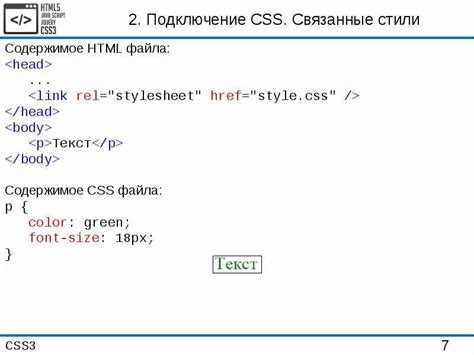
Выбор шрифта напрямую влияет на читаемость и визуальное восприятие веб-страницы. В HTML шрифты можно подключать через встроенные, системные или веб-шрифты, при этом каждый способ имеет свои особенности совместимости и производительности. Использование системных шрифтов гарантирует мгновенную загрузку, но ограничивает дизайнерские возможности.
Веб-шрифты подключаются через сервисы вроде Google Fonts или через локальные файлы формата .woff и .woff2. Для подключения через Google Fonts достаточно вставить тег <link href=»URL_шрифта» rel=»stylesheet»> в head документа и использовать имя шрифта в CSS с помощью свойства font-family. Локальные шрифты подключаются через @font-face с указанием пути к файлу, формата и веса.
При выборе метода подключения важно учитывать скорость загрузки и поддержку браузеров. Формат .woff2 обеспечивает лучшую компрессию и поддерживается современными браузерами, в то время как .ttf и .otf совместимы с более старыми версиями. Рекомендуется всегда указывать запасной шрифт через font-family, чтобы избежать некорректного отображения текста при проблемах с загрузкой основного шрифта.
Правильная организация шрифтового кода повышает стабильность отображения и уменьшает нагрузку на сервер. Использование локальных и веб-шрифтов одновременно позволяет обеспечить баланс между дизайном и производительностью, особенно на мобильных устройствах с ограниченной скоростью интернета.
Выбор шрифта для веб-проекта
При выборе шрифта важно учитывать читаемость, совместимость и контекст использования. Для текста основного контента оптимальны гарнитуры с засечками (serif) для длинных абзацев или без засечек (sans-serif) для краткой информации и интерфейсов. Например, для статей подходят шрифты Georgia и Times New Roman, а для кнопок и меню – Roboto, Open Sans, Lato.
Необходимо учитывать поддержку браузеров и операционных систем. Google Fonts предлагает шрифты с широким покрытием, включая кириллицу, что минимизирует проблемы с отображением на разных устройствах. Для критичных элементов интерфейса используйте системные шрифты как запасные, указав их через CSS: font-family: ‘Roboto’, Arial, sans-serif;
Размер шрифта должен соответствовать целевой аудитории и устройству. Для мобильных устройств рекомендуется минимум 16px для основного текста, для десктопа – 18–20px. Межстрочный интервал (line-height) оптимально устанавливать в диапазоне 1.4–1.6, чтобы улучшить восприятие длинных текстов.
Контраст шрифта с фоном влияет на доступность. WCAG рекомендует соотношение не менее 4.5:1 для нормального текста. Используйте темный текст на светлом фоне или наоборот, избегая ярких цветовых комбинаций, которые затрудняют чтение.
Для веб-проектов с мультиязычным контентом проверяйте поддержку необходимых символов. Например, шрифты Noto Sans и Noto Serif покрывают более 100 языков и обеспечивают единообразие оформления текста.
При выборе декоративных шрифтов ограничивайте их использование заголовками или акцентными блоками, чтобы не перегружать визуальное восприятие. Следите за балансом между оригинальностью и функциональностью, ориентируясь на цели проекта и удобство пользователей.
Подключение системных шрифтов через CSS
Пример базового подключения системного шрифта:
body { font-family: "Segoe UI", Tahoma, Geneva, Verdana, sans-serif; }
В этом примере перечислены несколько вариантов шрифтов через запятую. Браузер выберет первый доступный на устройстве пользователя. Последний вариант sans-serif выступает запасным, обеспечивая корректное отображение при отсутствии перечисленных шрифтов.
Ниже приведена таблица с популярными системными шрифтами по платформам:
| Платформа | Рекомендованные шрифты | Категория |
|---|---|---|
| Windows | Segoe UI, Tahoma, Verdana | Sans-serif |
| macOS | San Francisco, Helvetica Neue, Geneva | Sans-serif |
| Linux | Ubuntu, DejaVu Sans, Liberation Sans | Sans-serif |
| iOS | San Francisco, Helvetica, Arial | Sans-serif |
| Android | Roboto, Noto Sans | Sans-serif |
Для корректного отображения текста на всех устройствах рекомендуется использовать стек шрифтов, начиная с наиболее предпочтительного и заканчивая общим типом (serif, sans-serif, monospace). Это минимизирует риск замены шрифта браузером и сохраняет читаемость.
При использовании системных шрифтов можно задавать дополнительные параметры через CSS: font-weight, font-style, font-variant. Например:
h1 { font-family: "Segoe UI", Tahoma, sans-serif; font-weight: 600; font-style: italic; }
Такой подход позволяет поддерживать визуальное разнообразие текста без загрузки внешних ресурсов и снижает нагрузку на сеть.
Использование веб-шрифтов с Google Fonts
Google Fonts предоставляет библиотеку более чем из 1 600 шрифтов, доступных для бесплатного использования в веб-проектах. Подключение осуществляется через ссылку в <head> или импорт в CSS.
Для подключения через HTML используйте тег <link>:
<link href="https://fonts.googleapis.com/css2?family=Roboto:wght@400;700&display=swap" rel="stylesheet">
Параметры ссылки:
- family – имя шрифта и диапазон начертаний. Например,
Roboto:wght@400;700подключает обычный и жирный варианты. - display – способ отображения текста при загрузке шрифта. Значение
swapобеспечивает мгновенное отображение текста с заменой на шрифт после загрузки.
Для подключения через CSS используйте директиву @import:
@import url('https://fonts.googleapis.com/css2?family=Roboto:wght@400;700&display=swap');
После подключения шрифта применяйте его в CSS через свойство font-family:
body {
font-family: 'Roboto', sans-serif;
font-weight: 400;
}
Рекомендации по использованию Google Fonts:
- Подключайте только нужные начертания и стили, чтобы уменьшить время загрузки.
- Используйте
font-display: swapдля улучшения производительности и предотвращения «невидимого текста». - Проверяйте совместимость шрифтов с кириллицей, если проект на русском языке.
- Для критических элементов можно хранить локальную копию шрифта для ускорения загрузки.
Google Fonts поддерживает переменные шрифты (variable fonts), которые позволяют плавно изменять вес и ширину текста через CSS. Пример подключения:
<link href="https://fonts.googleapis.com/css2?family=Roboto+Flex:opsz,wght@8..144,100..1000&display=swap" rel="stylesheet">
Использование веб-шрифтов Google Fonts повышает читаемость и визуальную привлекательность сайта без необходимости хранения файлов на сервере.
Импорт шрифтов через @font-face
Для подключения пользовательских шрифтов в HTML используется правило CSS @font-face. Оно позволяет указать имя шрифта и путь к файлу, доступному на сервере или через URL. Пример базового синтаксиса:
@font-face { font-family: "MyFont"; src: url("fonts/MyFont.woff2") format("woff2"); font-weight: 400; font-style: normal; }
Рекомендуется указывать несколько форматов файлов для кроссбраузерной совместимости: woff2, woff, ttf и eot. Формат woff2 обеспечивает лучшее сжатие и поддержку современных браузеров.
Параметр font-weight определяет толщину шрифта, а font-style – его наклон. Для разных начертаний создаются отдельные правила @font-face с одинаковым font-family и уникальными весами и стилями.
Если шрифт используется только локально, указывайте относительный путь к файлу. Для удаленных ресурсов – абсолютный URL. Чтобы ускорить загрузку, подключение шрифта лучше размещать в начале CSS-файла.
Для резервного использования добавляйте font-display. Значение swap обеспечивает отображение текста системным шрифтом до загрузки кастомного, исключая «невидимый текст».
Пример расширенного подключения с резервом и несколькими форматами:
@font-face { font-family: "MyFont"; src: url("fonts/MyFont.woff2") format("woff2"), url("fonts/MyFont.woff") format("woff"); font-weight: 400; font-style: normal; font-display: swap; }
Использование @font-face позволяет полностью контролировать набор шрифтов на сайте без зависимости от внешних сервисов, обеспечивая единообразие отображения текста во всех браузерах и устройствах.
Форматы файлов шрифтов и их поддержка браузерами
Наиболее распространённые форматы веб-шрифтов включают TTF, OTF, WOFF, WOFF2 и SVG. TTF (TrueType) поддерживается всеми современными браузерами, но имеет больший размер и медленнее загружается. OTF (OpenType) аналогичен TTF, отличается расширенными возможностями кернинга и поддержкой лигатур, совместимость с браузерами также высокая.
WOFF (Web Open Font Format) оптимизирован для веба, сжат и быстрее загружается. Все актуальные версии Chrome, Firefox, Safari, Edge и Opera полностью поддерживают WOFF. WOFF2 – усовершенствованная версия с ещё более эффективным сжатием, поддержка начинается с Chrome 36+, Firefox 35+, Edge 14+, Safari 10+. Для старых браузеров рекомендуется предусматривать резервные форматы TTF или OTF.
SVG-шрифты используются преимущественно в старых версиях iOS (до iOS 4.2) для корректного отображения на устройствах Apple. Их использование в современных проектах нецелесообразно из-за ограниченной поддержки и устаревших стандартов.
При подключении веб-шрифтов следует использовать последовательность форматов: WOFF2 → WOFF → TTF/OTF. Такая схема обеспечивает минимальный размер загрузки для современных браузеров и резервную совместимость с устаревшими.
Дополнительно рекомендуется проверять поддержку форматов через Can I Use или аналогичные ресурсы и использовать атрибут font-display: swap в CSS для предотвращения задержки рендеринга текста при загрузке шрифта.
Настройка начертаний и размеров шрифта в CSS
В CSS начертание и размер шрифта задаются с помощью свойств font-weight, font-style, font-size и line-height. Каждое из них имеет конкретные значения и рекомендации для использования.
Начертание шрифта:
font-weight– определяет толщину символов. Значения:- Нумерические:
100(тонкий) –900(черный) - Ключевые:
normal(обычный),bold(жирный),bolder,lighter
- Нумерические:
font-style– задает стиль текста:normal– обычное начертаниеitalic– курсивoblique– наклонное, менее выраженное, чем курсив
Размер шрифта:
font-size– регулирует высоту символов:- Абсолютные значения:
px,pt - Относительные значения:
em,rem,% - Рекомендуем: базовый текст
16px, заголовки1.25em–2emот базового
- Абсолютные значения:
line-height– расстояние между строками:- Оптимально:
1.4–1.6для основного текста - Для заголовков можно уменьшить до
1.2при компактном дизайне
- Оптимально:
Практические рекомендации:
- Используйте числовые значения
font-weightдля точного контроля толщины, особенно при подключении кастомных шрифтов. - Не смешивайте
italicиobliqueбез необходимости – различие визуально едва заметно, но влияет на читаемость. - Выбирайте
remдляfont-sizeу элементов интерфейса, чтобы поддерживать масштабирование текста пользователем. - Устанавливайте
line-heightотдельно отfont-sizeдля гибкого управления интервалами, а не через единое свойствоpaddingилиmargin.
Сочетание этих свойств позволяет создавать четкую иерархию текста, улучшать читаемость и адаптировать шрифты под разные устройства без потери визуальной гармонии.
Оптимизация загрузки шрифтов на сайте
Используйте формат WOFF2 для всех веб-шрифтов: он обеспечивает компрессию до 30–40% по сравнению с WOFF и почти вдвое меньше, чем TTF, при идентичном визуальном отображении.
Подключайте шрифты через <link rel="preload" as="font" crossorigin>, чтобы браузер загружал их раньше CSS, сокращая время отображения текста.
Минимизируйте количество вариаций шрифтов: оставляйте только нужные веса и стили. Каждая лишняя вариация увеличивает общий вес страницы на 50–100 КБ.
Используйте свойство font-display: swap; в @font-face. Это позволяет браузеру показывать системный шрифт до полной загрузки веб-шрифта, предотвращая «невидимый текст» (FOIT).
Храните шрифты на CDN с HTTP/2 или QUIC, чтобы параллельно загружать несколько файлов, снижая задержки на 20–30%.
Оптимизируйте подмножества (subset) шрифтов, оставляя только используемые символы. Например, латиница и цифры для англоязычного интерфейса могут уменьшить размер файла до 70%.
Кэшируйте шрифты с заголовками Cache-Control: max-age=31536000 и immutable, чтобы повторные загрузки происходили только при обновлении файлов.
Проверяйте использование шрифтов через Lighthouse или WebPageTest: замеры FCP и LCP покажут, какие шрифты замедляют рендеринг.
Проверка корректности отображения шрифтов
Для проверки шрифтов используйте сочетание визуального и технического контроля. Начните с открытия страницы в нескольких браузерах: Chrome, Firefox, Safari и Edge. Убедитесь, что подключенные шрифты отображаются одинаково на всех платформах.
Проверяйте наличие fallback-шрифтов. Если основной шрифт не загрузился, текст должен корректно отображаться запасным вариантом. Для этого временно отключите загрузку основного шрифта через CSS, например, закомментировав правило @font-face.
Используйте инструмент разработчика браузера для контроля загрузки шрифтов. Вкладка Network показывает, были ли успешно загружены файлы шрифтов и какой формат использован (.woff, .woff2, .ttf, .eot). Обратите внимание на коды статуса: 200 – загрузка успешна, 404 или 403 – ошибка.
Проверяйте корректность отображения глифов и символов. Создайте тестовый блок с латиницей, кириллицей, цифрами и специальными символами. Убедитесь, что все символы рендерятся без искажений, перекрытий и разрывов.
Сверяйте межсимвольные интервалы и высоту строк. Разные браузеры могут по-разному интерпретировать line-height и letter-spacing. Настройте их в CSS и проверяйте визуально, чтобы текст не слипался и не разрывался.
Используйте специальные сервисы для тестирования веб-шрифтов, например, FontSquirrel Webfont Generator или Google Fonts Preview. Они позволяют проверить отображение шрифта на различных устройствах и разрешениях, выявляя проблемы совместимости.
Не забывайте проверять шрифты на мобильных устройствах. Часто десктопные настройки корректны, а на смартфонах или планшетах появляются искажения. Используйте эмуляторы или реальные устройства с разными ОС и браузерами.
Вопрос-ответ:
Каким образом можно подключить шрифты к HTML-странице?
Существует несколько способов добавить шрифты на веб-страницу. Один из них — использовать CSS-свойство @font-face, которое позволяет подключить файл шрифта напрямую с сервера. Также можно воспользоваться сторонними сервисами, например Google Fonts, которые предоставляют готовые ссылки для вставки в HTML через тег <link>. После подключения шрифта его можно применять к элементам страницы с помощью свойства font-family.
Какие форматы шрифтов лучше использовать для веб-сайта?
Для веб-страниц обычно применяют форматы WOFF и WOFF2, так как они сжаты и поддерживаются современными браузерами. Формат TTF также работает, но может быть тяжелее по размеру, а SVG используется редко. Для максимальной совместимости иногда подключают несколько форматов одновременно, чтобы браузеры могли выбрать подходящий.
Можно ли использовать шрифты, которые хранятся на локальном компьютере, без загрузки их на сервер?
Да, это возможно с помощью локальных ссылок в CSS через @font-face и указания пути к файлу шрифта. Однако такой метод ограничен браузером и системой пользователя: если путь указан неверно или файл недоступен, шрифт не отобразится. Поэтому для надежности обычно шрифты размещают на сервере сайта или используют облачные сервисы.
Как применить подключенный шрифт к отдельным элементам HTML?
После подключения шрифта через CSS его можно назначить конкретным элементам с помощью свойства font-family. Например, если шрифт назван «CustomFont», можно написать: h1 { font-family: 'CustomFont', sans-serif; }. Это применит выбранный шрифт к заголовкам <h1>. В качестве запасного шрифта указывают стандартный, чтобы текст отображался, если основной шрифт недоступен.